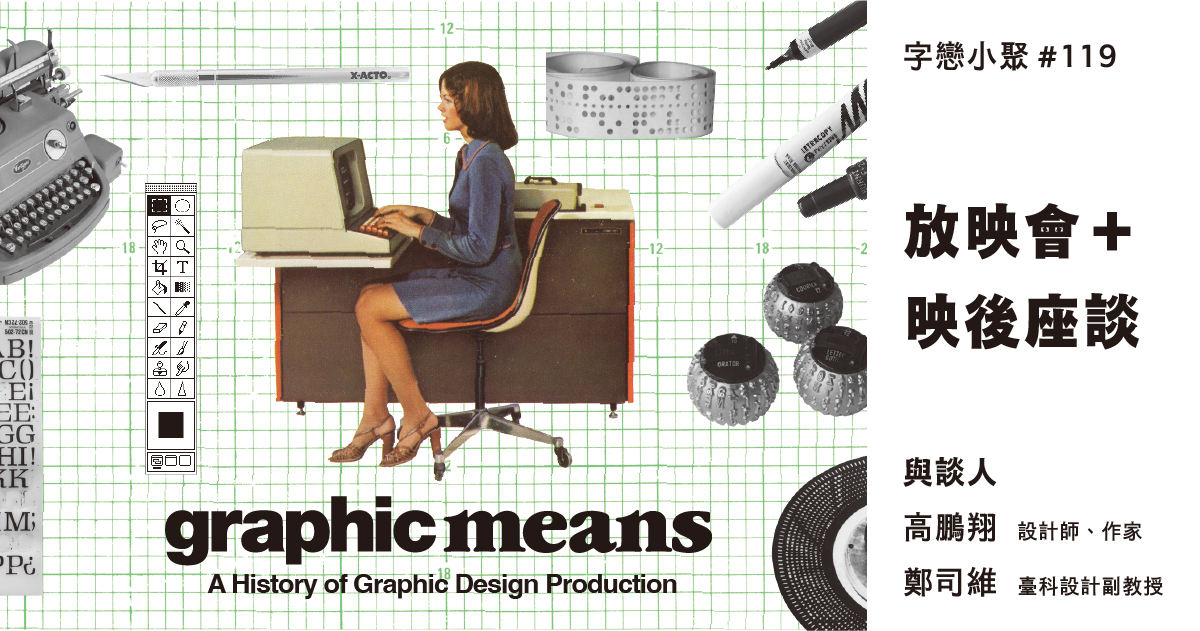
字戀小聚 #119|GRAPHIC MEANS 放映會+映後座談
距今約三十年前,桌上型電腦徹底翻轉了平面設計產業的樣貌。而在那之前的數十年間,靠的是無數勞動者的巧手,以及形形色色的精巧機具,將文字與圖像一一拼貼於工整繕製的貼版上,才得以送印付梓。
紀錄片《Graphic Means》帶領觀眾回顧 1950 年代至 1990 年代的平面設計製作史——從鑄字排版機到照相排版,從手工貼版到數位 PDF,見證這場產業技術的世代交替。
紀錄片以歐美世界為主軸,本場字戀小聚將帶來台灣經驗的觀點。
• GRAPHIC MEANS: A History of Graphic Design Production, 2016
• 導演:Briar Levit
• 與談人:高鵬翔(《臺灣活版時代》作者)、鄭司維(台科設計系專技副教授)